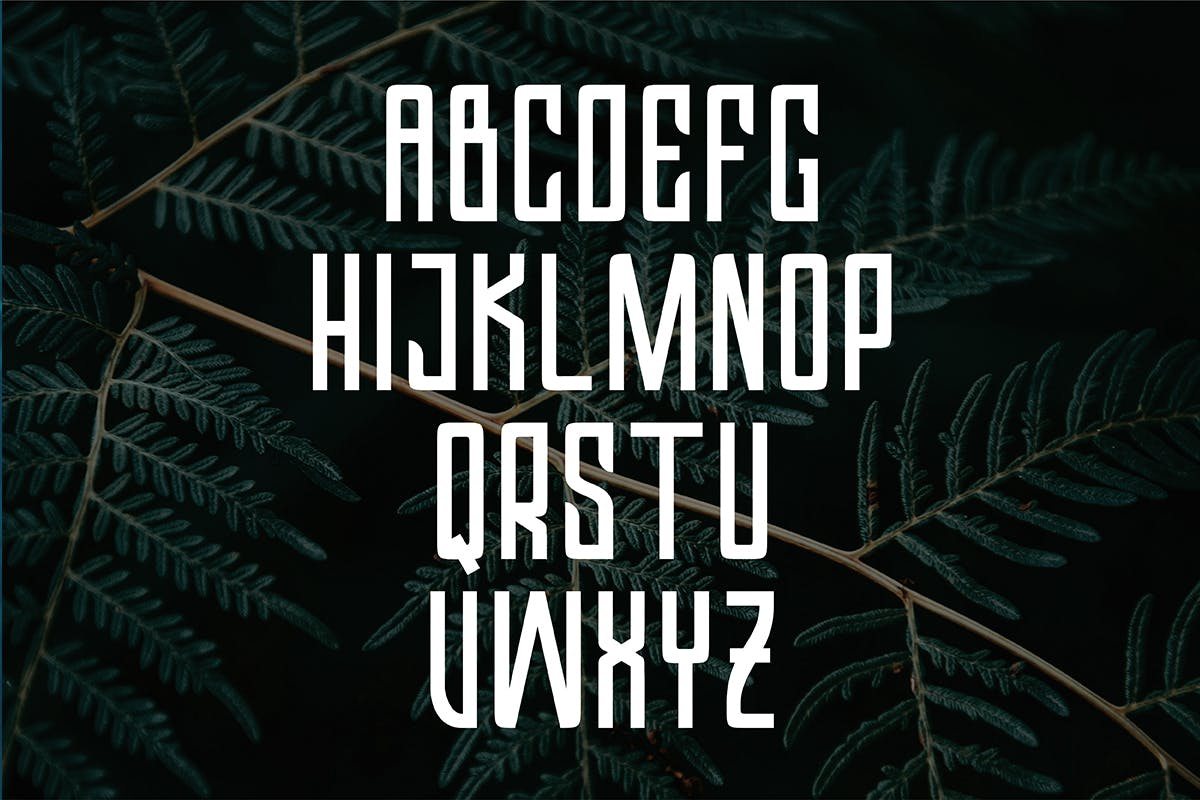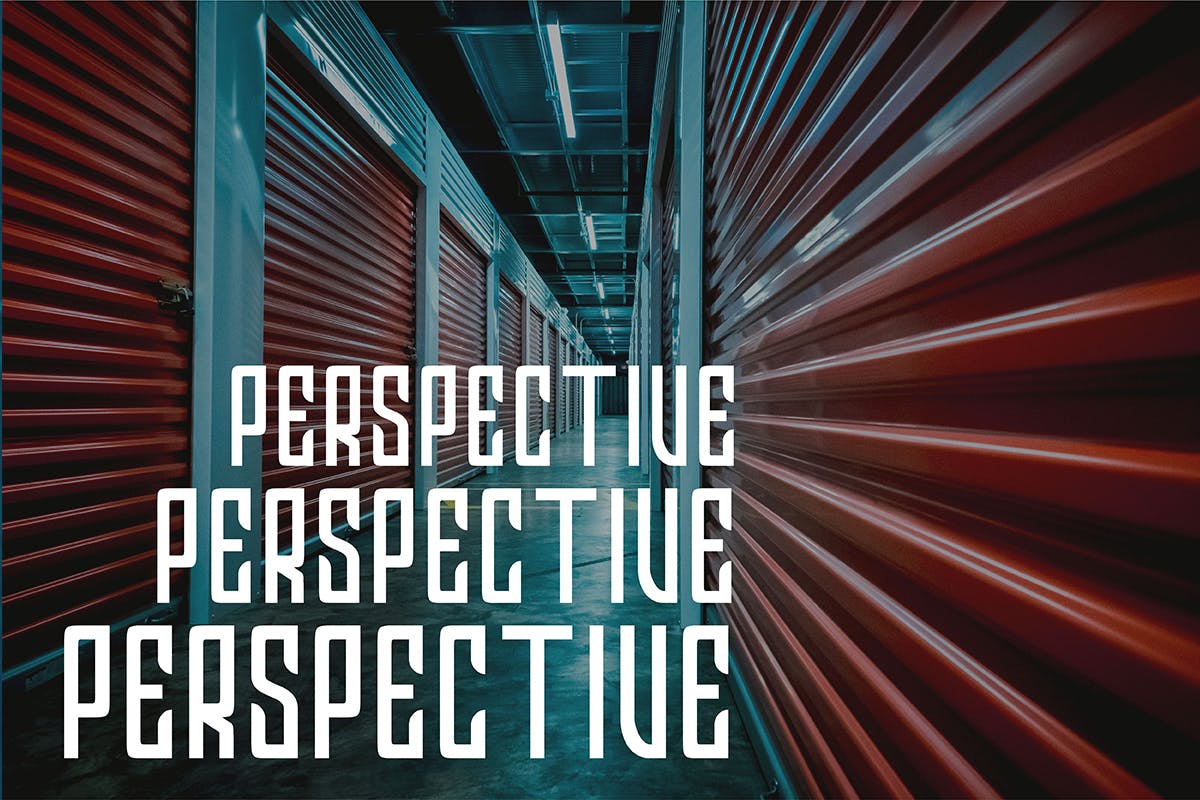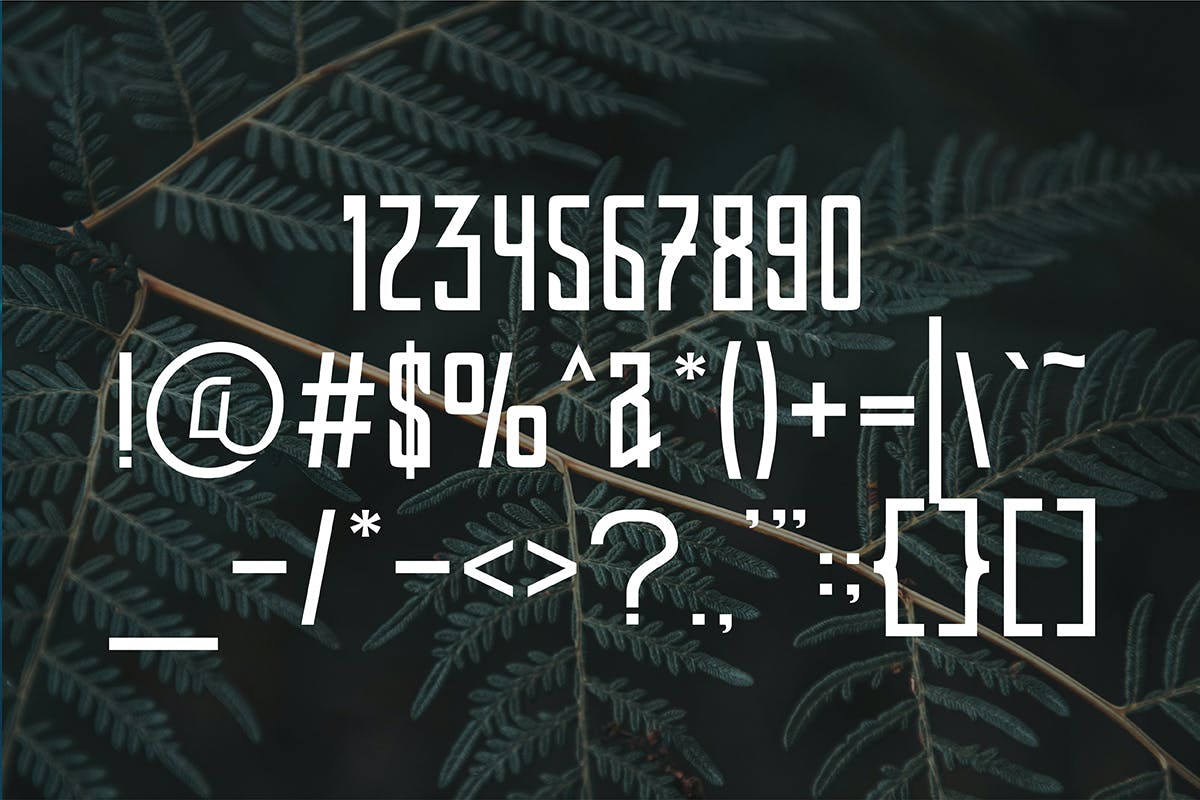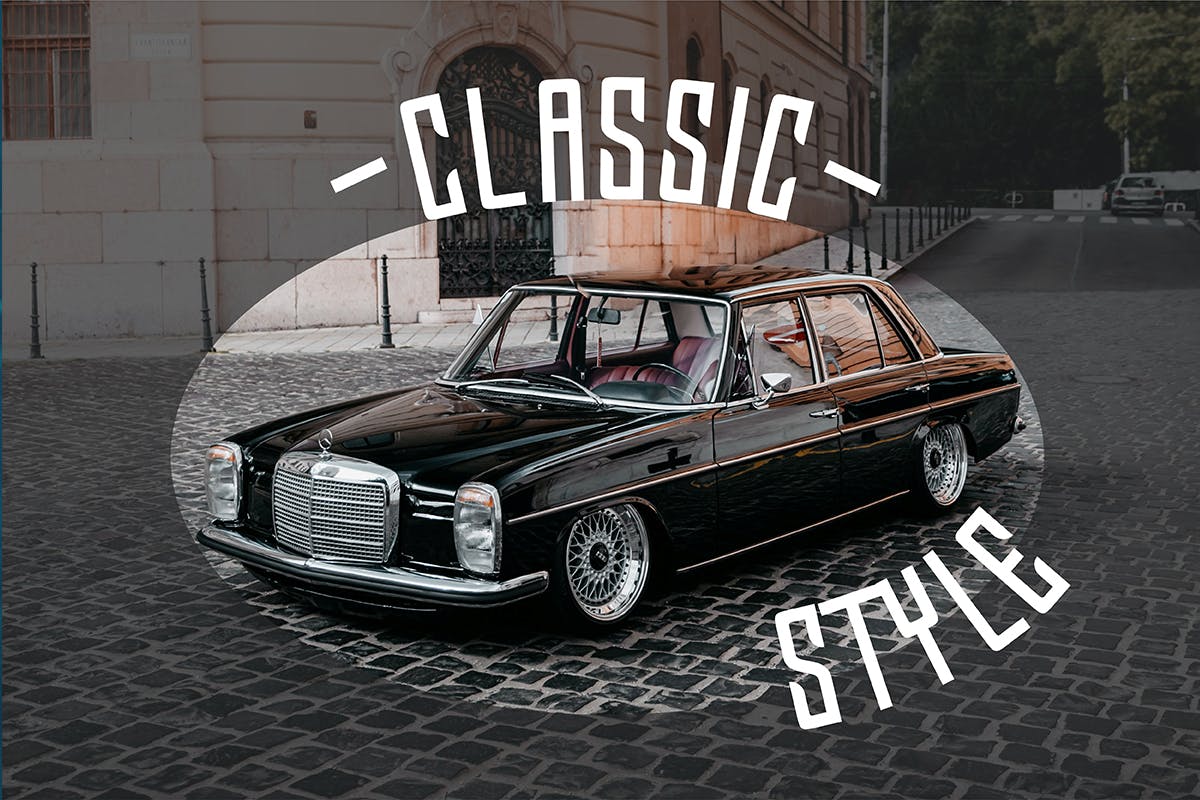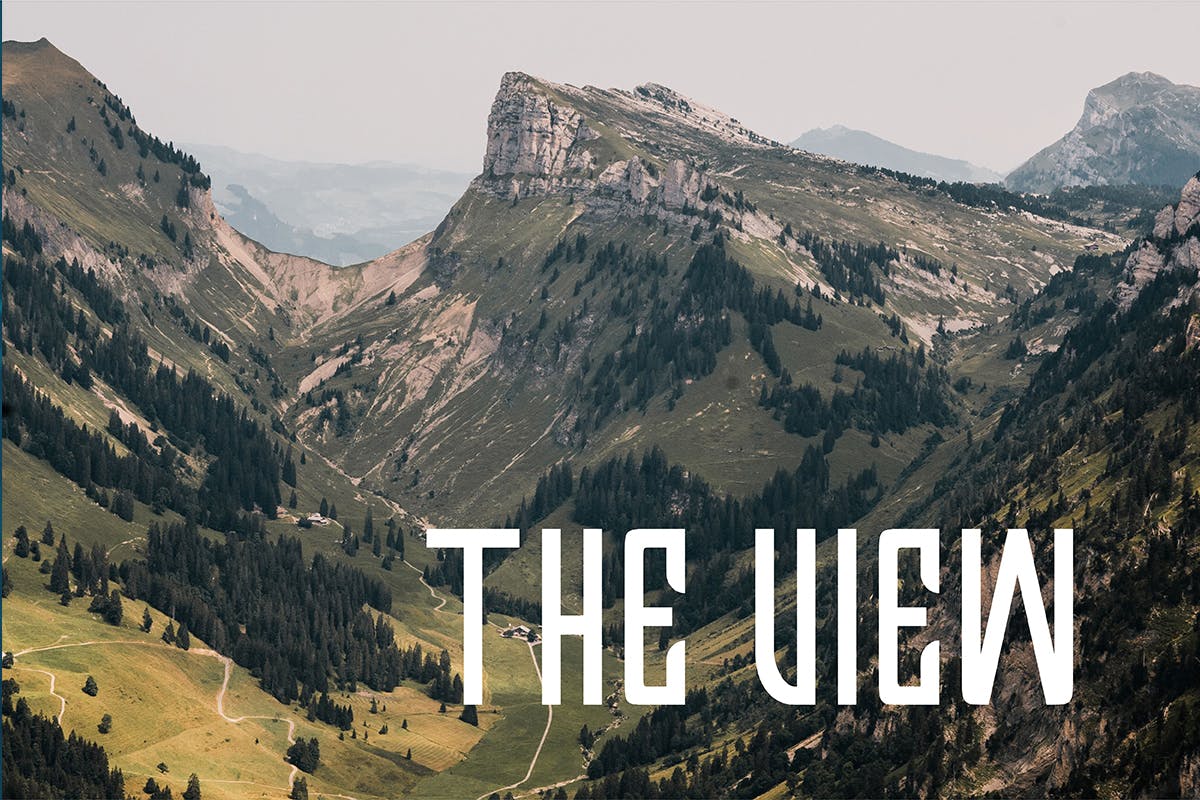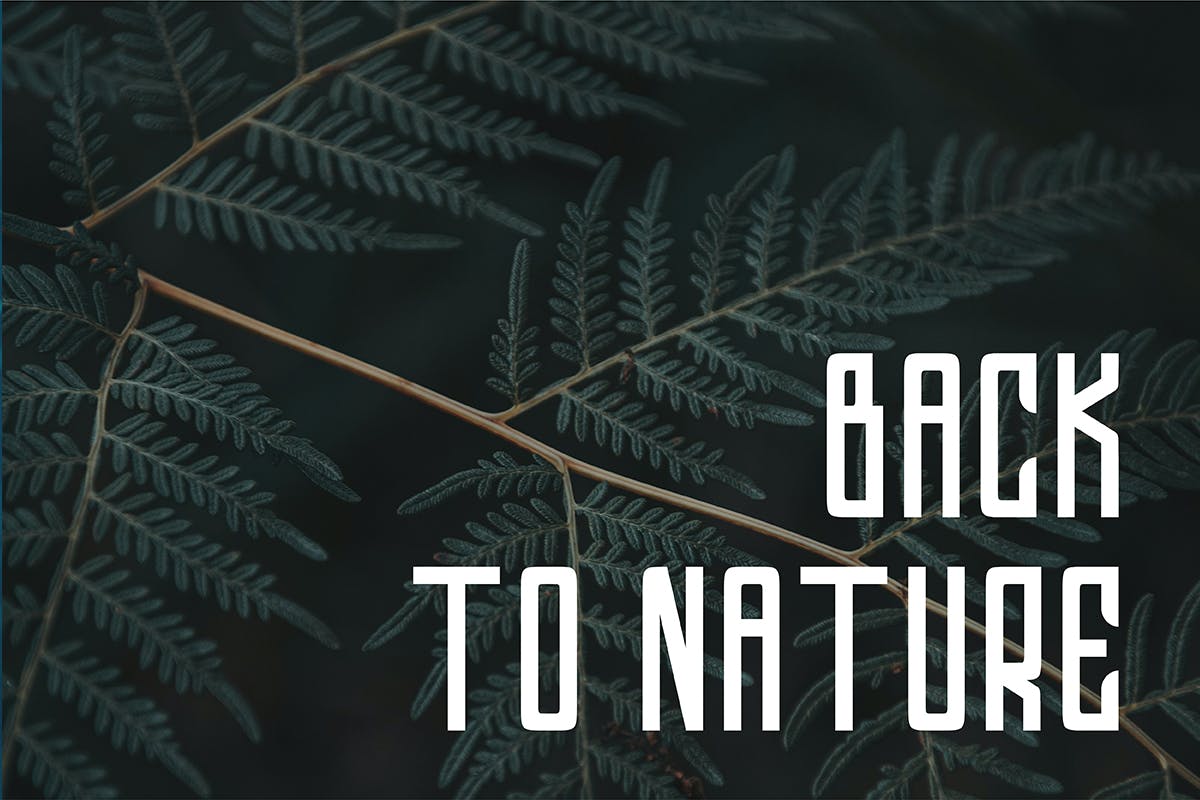
فونتهای Valkrye شامل حروف بزرگ، اعداد و مجموعهای بزرگ از نشانهها میباشد. این فونت بدون سر (sans serif) در سبک مدرن طراحی شده است. این فونت برای طراحی پوستر، وبسایت، برندینگ، تصاویر، آرمها و بسیاری از پروژههای دیگر مناسب است.